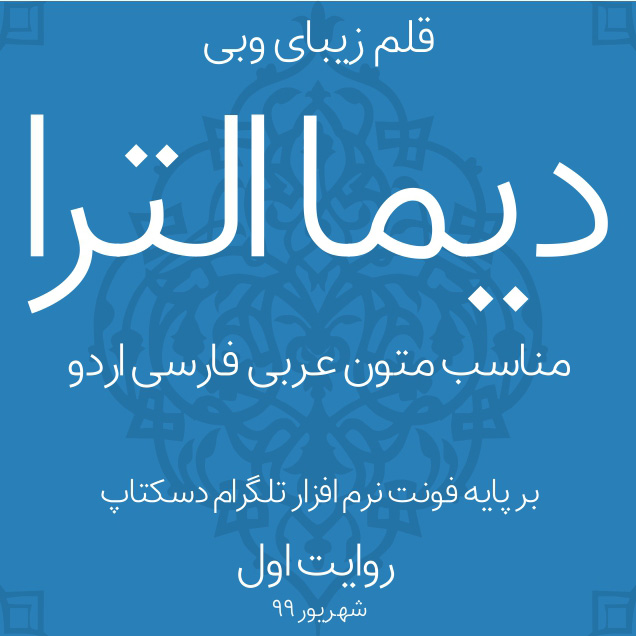
فونت دیما الترا یا دیما اولترا در اصل یک وب فونت فارسی است که اساس فونت تلگرام دسکتاپ طراحی شده، این فونت 4 وزن دارد، هم اکنون وزن Light به صورت حمایتی منتشر شده، جناب روح الله بلوردی ذکر کرد: اگر سقف حمایت این فونت پر شود آن را به صورت رایگان منتشر میکنیم، و اگر از آن استقبال شود سایر وزن ها رو منتشر میکنیم
پیش نمایش فونت دیما الترا